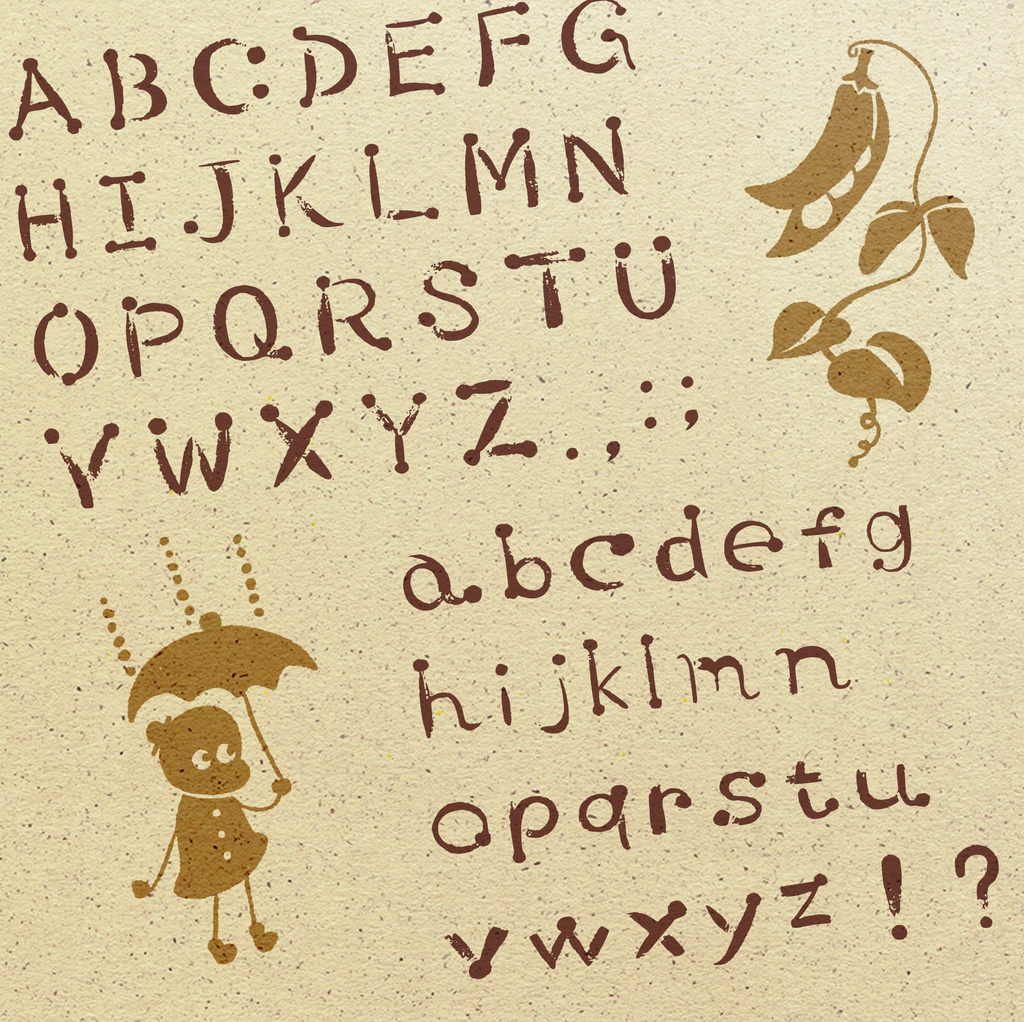
【英字フリーフォント/Free font】beenフォント
beenフォント【英字フリーフォント/Free Font】 商用&個人で使用できる英語フォントです。 同人誌やZINE、雑誌、ポートフォリオ等にお使い頂けます。 【内容】 A~Zまでの大文字、小文字アルファベットおよび記号 ※数字は含まれておりません ホームページのリニューアル記念として、無料で配布致します! 著作権は放棄していませんので、以下の規約を守ってお使い下さい。 /////////// ・フォントデータの複製、改変、再配布、再販売などは禁止させて頂きます。 ・こちらのフォントを使用した際のトラブル(PCの誤作動やウィルス感染、それに伴う故障など)については責任を負いかねますのでご了承下さい。 ・反社会的な内容の作品・広告等への使用は禁止させて頂きます。 ○商用でお使い頂く際にも、連絡は必要ありません。 製作者 2019(c) Miki Kuri twitter/@umaimesitaberu